终于,Flutter 修复 Android 中文字体异常,但是很草台,不知怎么吐槽
半年了,Flutter 终于修复了 3.38 带来的一个奇葩问题,在某些 Android 设备上,如果对比会发现,中文字体和之前版本不一样了,当然不是说完全渲染不对,而是字体变了:
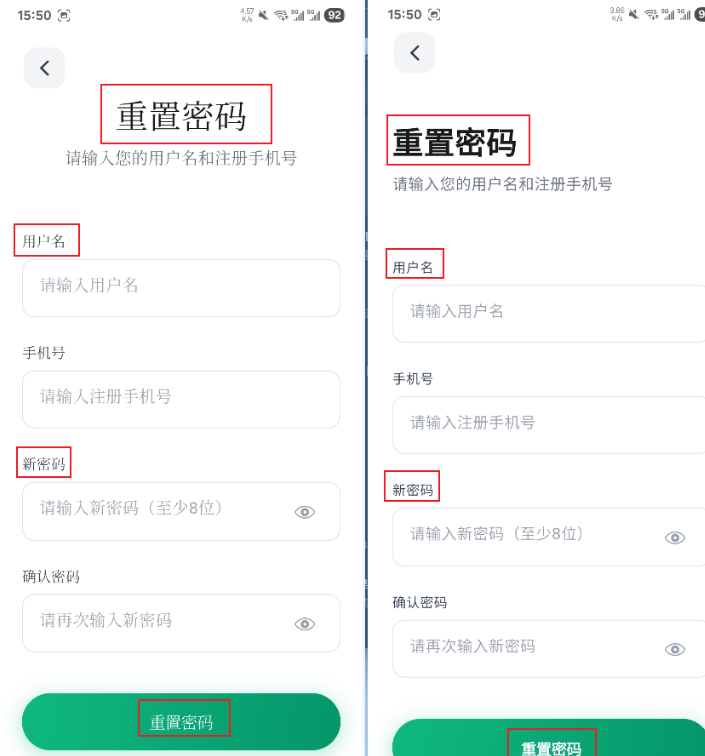
这个问题其实是因为中文字体从系统「默认的无衬线体」,变成了明显偏「宋体风格的衬线体」,问题主要集中在部分三星、OPPO、OnePlus 等设备。
所以它不是必现。
而这个问题恶心在于,其实 Flutter 在这里什么都没改,问题其实是 Skia 引起的,但是又不是完全 Skia 的问题,因为 Flutter 在 3.38 更新了 Skia 的版本,而 Skia 在这个新版本里,对 Android 字体回退逻辑发生了一次重构,而这次重构改变了 find_family_style_character 在某些场景下选择 fallback 字体的顺序:
你说 Flutter 不是 Impeller 了?为什么还 Skia ?这个问题其实我们说过很多次了,在字体,字形选择和字体排版等场景,Flutter 还是依赖 Skia 实现,只是最终渲染的是 Impeller 。
简单来说就是,Flutter 3.38 升级了 Skia,而 Skia 的 a918c0e 重构了 Android 字体搜索逻辑:当搜索过程走到 familyName 为空的路径时,新逻辑跳过了 fFallbackFor 的匹配检查,然后直接使用了「回退列表」里第一个中文字体。
而在一些设备上,这个第一个被命中的字体刚好是 NotoSerifCJK-Regular.ttc,它是衬线体,所以这时候中文就被渲染成了宋体风格。
听起来太抽象了?没事,后面聊聊就懂了,因为懂了之后你会觉得更抽象。
举个例子,在 Flutter 这段代码,虽然你写了 Roboto ,但是 Roboto 本身不包含中文字体,所以当 Flutter 要渲染「重」这个字时,底层会进入 Android 字体 fallback 机制:
)当前 Roboto 字体没有这个字形,所以需要去系统配置里找一个可以显示该字符的「后备字体」,而在 Android 上,这部分逻辑由 Skia 的 SkFontMgr_android.cpp 负责,其中关键函数就是 find_family_style_character:
在字体列表里找一个既符合当前字族(Group)约束、又包含目标字符的字体。
这里有两个关键概念:
- 一个是
familyName,也就是当前希望匹配的目标族名,比如Roboto、serif,或者空字符串 - 另一个是字体配置里的
fFallbackFor,它表示「这个字体是给哪个字族做后备的」
这里以三星设备上的典型配置为例,系统里可能同时存在两个 CJK 字体:
- 一个是无衬线体
SECCJK-Regular.ttc,它的fFallbackFor为空,表示它是通用后备 - 另一个是衬线体
NotoSerifCJK-Regular.ttc,它声明fFallbackFor = 'serif',表示它原则上应该只给 serif 字族做后备
</family>这里的关键就是,SECCJK-Regular.ttc 是通用 fallback,适合 Roboto 这种默认无衬线场景下兜底中文,而 NotoSerifCJK-Regular.ttc 是 serif 专用 fallback,只有明确要求 serif 风格时才应该使用。
但是问题就在这里:Skia 这个 Bug 版本,在优化匹配逻辑的时候,直接忽略了
fFallbackFor,所以每一个重构的初衷都是好的,自己力不能及,总会带来坑坑洼洼。
而在以前没问题的版本里,即使 familyName 为空,也会继续检查 fFallbackFor ,在 Flutter 3.35 对应的 Skia 旧逻辑里,当 familyName = '' 时,Skia 会遍历回退列表做二次匹配。
比如老版本里,它先看到 NotoSerifCJK-Regular.ttc,发现它的 fFallbackFor = 'serif',并不等于空字符串,于是跳过。
然后继续往后找,看到 SECCJK-Regular.ttc,它的 fFallbackFor = '',匹配空 familyName,而且包含“重”这个汉字,于是返回正确字体。
但是 3.38 开始,Flutter 对应使用的新的 Skia 版本里,当 familyName 为空时,它因为忽略 fFallbackFor ,所以直接就返回了 fallback 的第一个。
回到 Skia commit a918c0e 这个修改,它起初的目的是重构字体搜索路径,让搜索更完整,但在重构过程中,不知觉的引入了这个其他 bug :当 familyName 为空时,就跳过 fFallbackFor 匹配检查。
这在一些极端兜底场景里看起来合理,因为空 familyName 可以被理解成“找任何能显示这个字符的字体”,但是它在 Android CJK 字体配置就产生了副作用:
NotoSerifCJK-Regular.ttc虽然只是 serif 专用后备,但它确实包含中文,如果它在某个无语言约束或空familyName路径里排在前面,就会被直接返回,这也是为什么只有某些机器才会的原因,这个 Bug 取决于厂家 fallback 自己排列的顺序。
关键差异只有一个:当 familyName = '' 时,到底还要不要继续检查 fFallbackFor,在旧逻辑继续检查,所以会跳过 fFallbackFor = 'serif' 的专用字体,而在 Bug 逻辑里会跳过检查,所以 NotoSerifCJK 被直接返回。
当然,这里还有一个为什么会空字符串?因为前几轮搜索没找到时,Skia 内部会用空 familyName 再试一次"无差别全局搜索"。
而一开始大家发现,只要在 MaterialApp 里面显式配置中文 locale , Flutter 就能正确识别语言环境,从实现正常渲染:
)但是后来又发现,当然系统语言为英文时,出现中文字体还是会 fallback 到错误字体上,因为根本原因还是在 Skia 层。
比如 Flutter 渲染文字时,最终会调用 Skia 的 onMatchFamilyStyleCharacter:
)而这里的 bcp47[] 这个语言标签数组,就是 locale 直接影响的东西,正常来说,如下代码所以,带语言标签的搜索(①)优先级高于空语言标签的兜底搜索(②),所以当 lang.getTag() 存在时,是可以匹配到正确的字体:
}但是 bcp47[] 里放什么,还取决于系统语言和 App 配置的 locale 的组合,而 bcp47[] 在组装时,代码路径会参考系统 locale ,某些系统下即使配置了 zh-CN,bcp47 数组里也不一定能正确传入 zh-Hans 标签 。
所以这个 Bug 不单单是 Flutter 版本带的 Skia 导致,而是由 Flutter 版本、Skia 版本、Android 系统字体配置、系统语言、应用 locale 等多个因素共同触发。
然后更抽象的来了,在第一次 Skia 侧做修复时(Fix SkFontMgr_Android fallback bb69b5b) ,只是把语义调整为“best match” ,让空 family name 时通用 fallback fonts 优先于 family-specific fallback fonts ,但是它忽略了 find_family_style_character 的搜索不是一个单阶段流程,它有多种匹配模式:
所以 Skia 又又又进行了第二次修改 (Adjust SkFontMgr_Android fallback order 2636871),这次修复后的逻辑核心是:
- 如果存在
fFallbackFor = ''的通用后备字体,就应该优先返回通用后备 - 只有在没有通用后备字体可以显示时,才把
fFallbackFor = 'serif'这类专用后备当成最后手段
所以这也是这个问题为什么修了这么久的原因,因为它是 Skia 带来的问题,你就只能等 Skia 团队修复,但是谁能想到,它还要修两次才修的好。
但是,严格来说这个 Bug 修的算快的,因为它不只是在 Flutter 上会有问题,如果是某个 Android 版本也引用了这个 Skia 提交,其实也会有类似问题,所以根据 Flutter 其他问题的时间周期来看,这个 Bug 修的算快了,因为它同时也影响了 Android 平台本身。
而目前这个修复的 Skia 版本已经合并到 3.43.0-0.3.pre ,所以下个版本 3.44 稳定版就可以直接 Fix 问题了,不得不说这个问题真的很抽象又恶心,最重要这个 Bug 出现的原因和修复过程也是很草台,同时也不得不感慨,字体问题永远是中文的痛处。